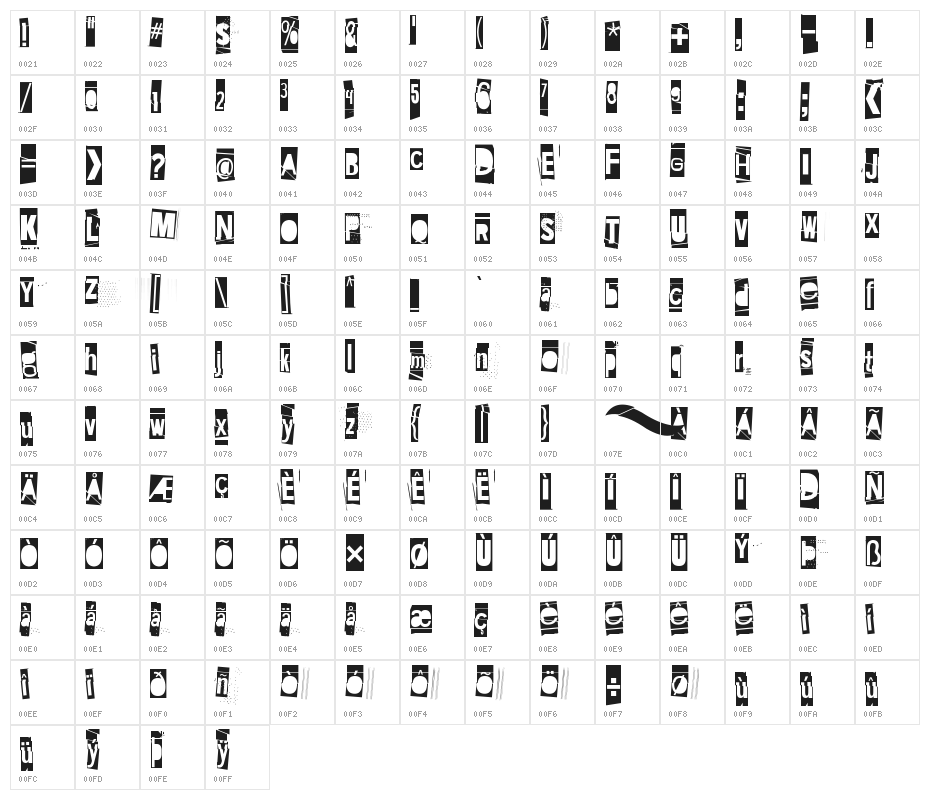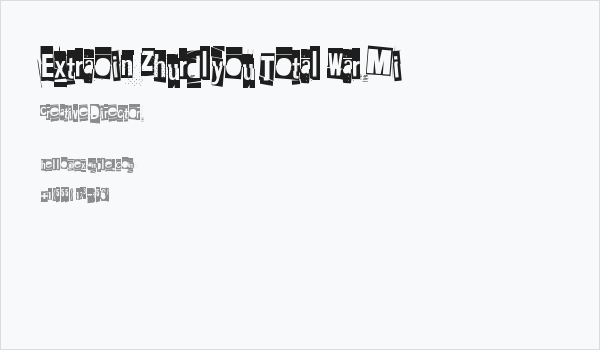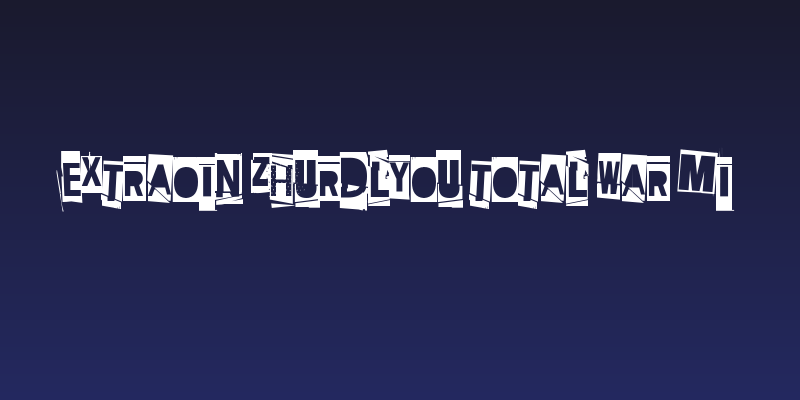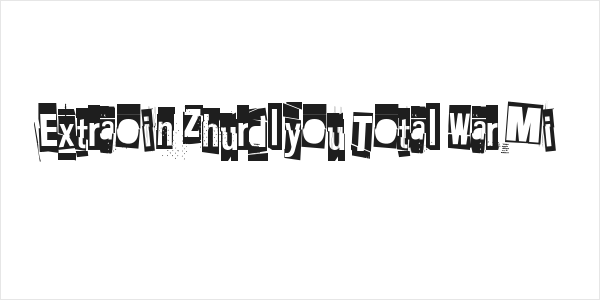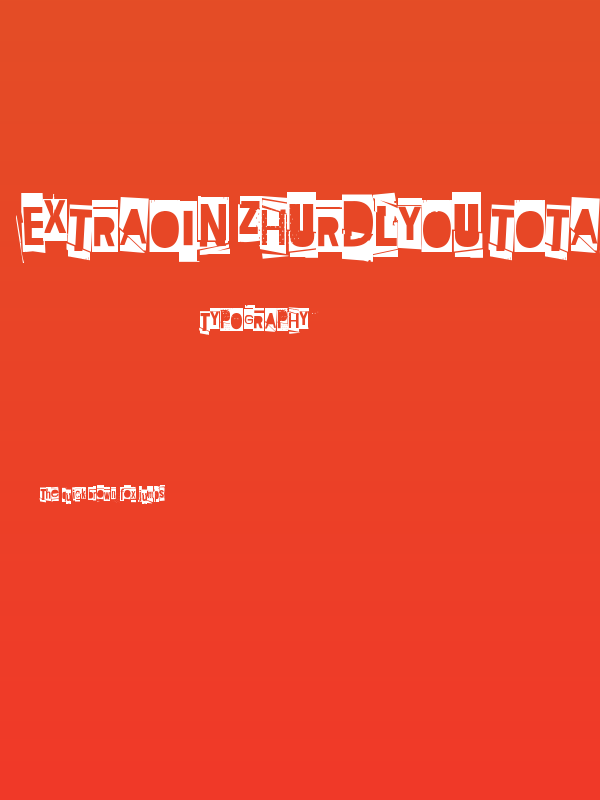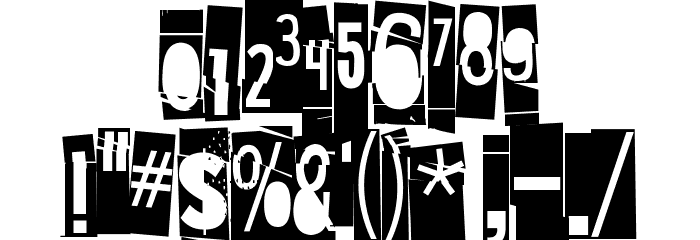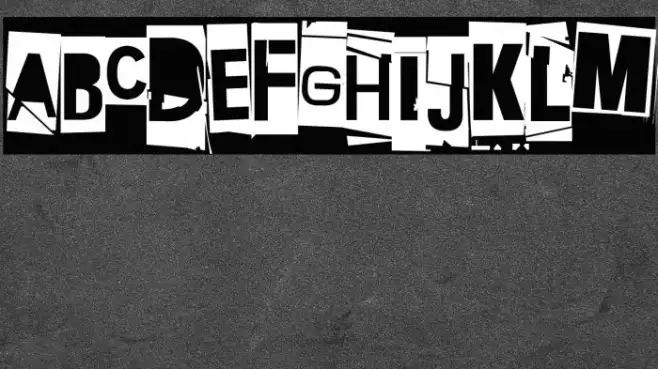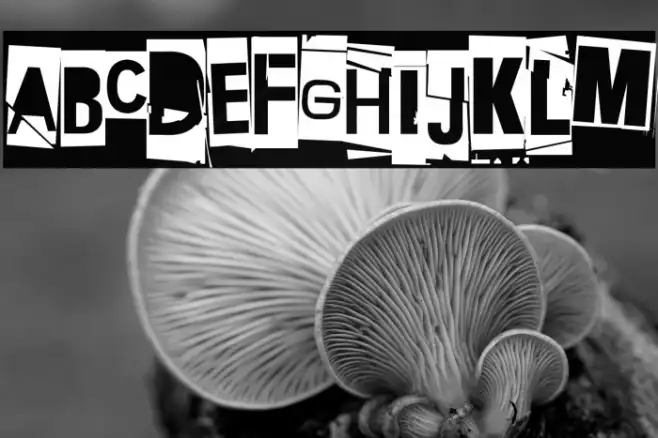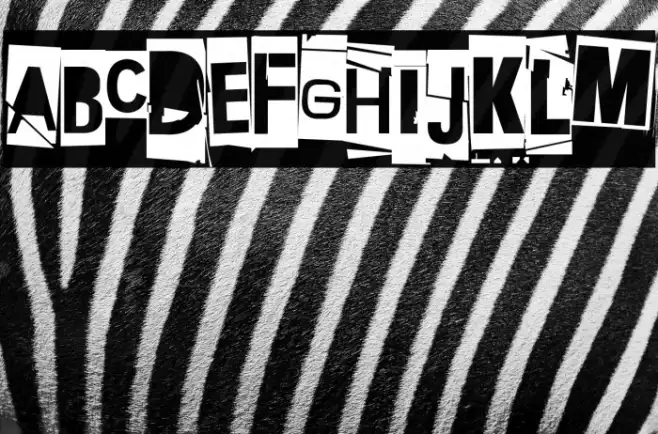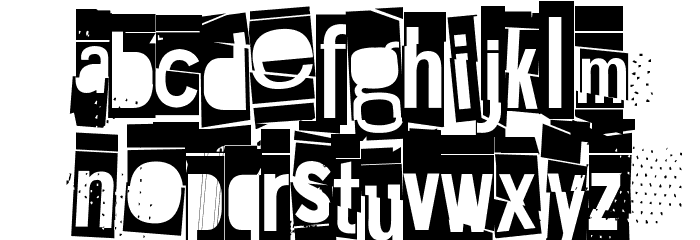
Extraoin Zhurdlyou Total War Mi Font
| Anwendungsfall | Headlines, Posters, Artistic Designs |
| Vorgeschlagene Projekte | Ideal for artistic projects, album covers, posters, and any design needing a bold, unconventional statement. |